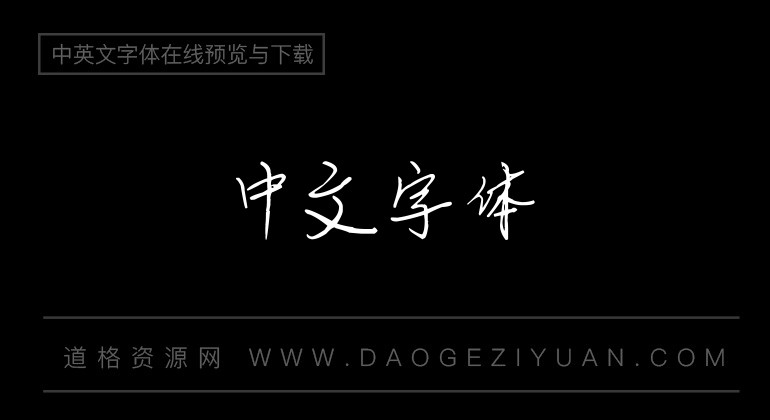
逐浪时尚钢笔体
逐浪时尚钢笔体字体是一款经典优雅的欧洲风格钢笔字体,它结合了传统的欧洲风格钢笔字体和现代时尚风格,让您的文字充满优雅和浪漫的气息。它的字形精确,细节丰富,笔画细腻,笔触柔和,字体清晰,具有良好的可读性,适用于各种文字排版,是您打造个性化文字的首选字体。
逐浪时尚钢笔体是一款非常不错的手写艺术字体,具有很好的视觉感,适合于文化类的宣传设计、商业类品牌的广告和产品包装设计以及个性化文字排版等较多场景。
逐浪时尚钢笔体字符映射图